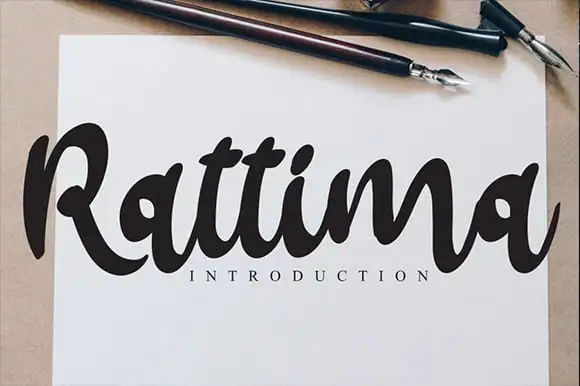
Rattima Bold Script Font – Download Grátis
A Rattima Bold Script Font oferece uma experiência visual única e sofisticada para designers e criadores de conteúdo. Este tipo digital se destaca por sua elegância e precisão, ideal tanto para estilos tradicionais quanto modernos de design. Seus traços bold proporcionam um impacto forte em qualquer projeto visual que exija um toque autêntico de escrita a mão. Perfeita para adicionar uma nota pessoal e única aos seus projetos, essa fonte é perfeitamente adequada para aplicações como displays na parede, convites casais, logotipos em postagens nas redes sociais, anúncios digitais, embalagens de produtos, designs dos produtos, selos, fotografia e até mesmo marcos nas imagens. Ela é uma escolha inovadora para qualquer trabalho que exija um toque refinado e autêntico. Com sua estética inspirada em escrita a mão, a Rattima Bold Script Font proporciona aos criadores de conteúdo o poder de personalizar seus projetos de forma única, garantindo um design que impressiona. Esta fonte é perfeita para quem busca trazer uma sensação pessoal e autêntica aos seus trabalhos visuais.